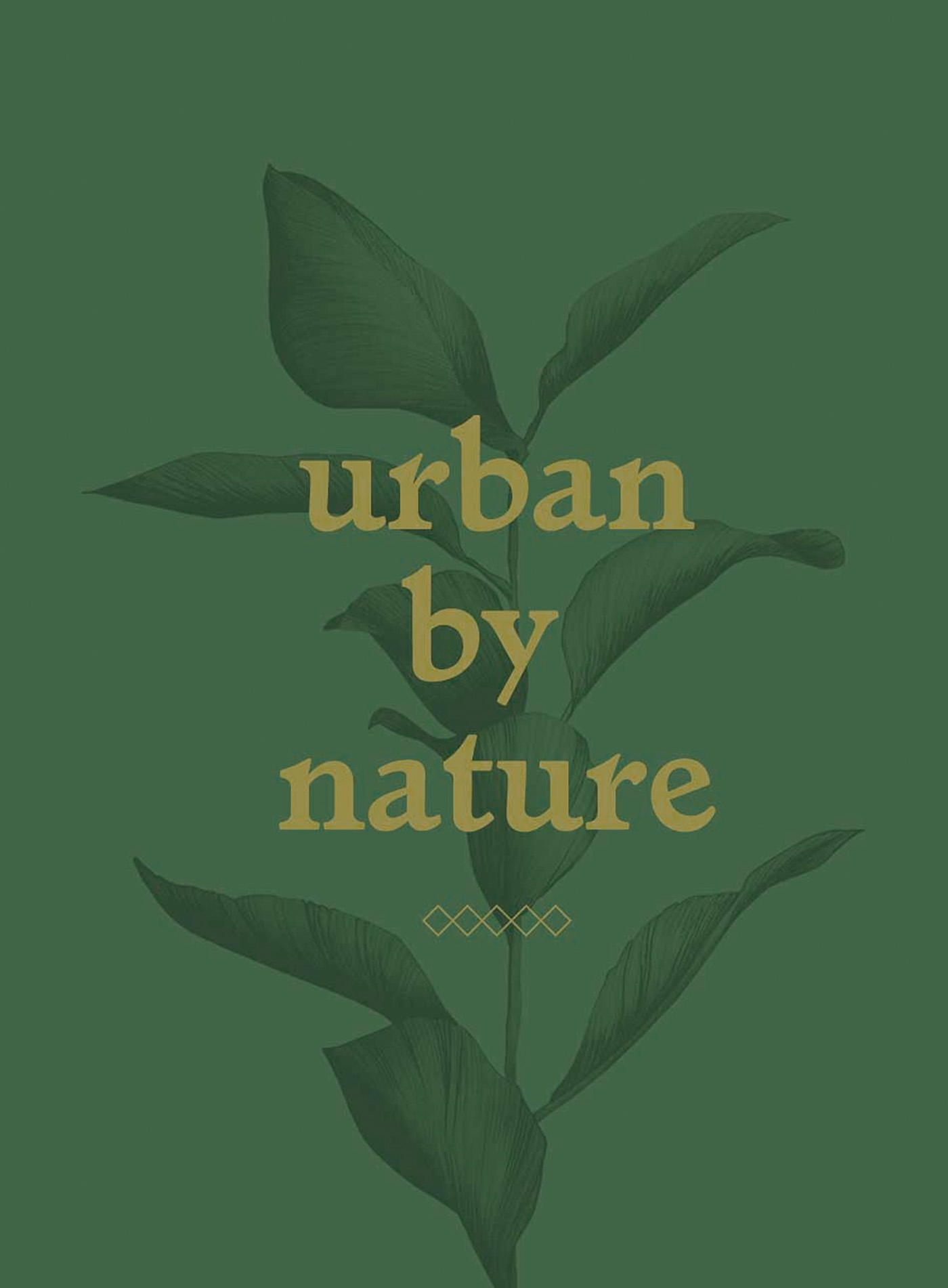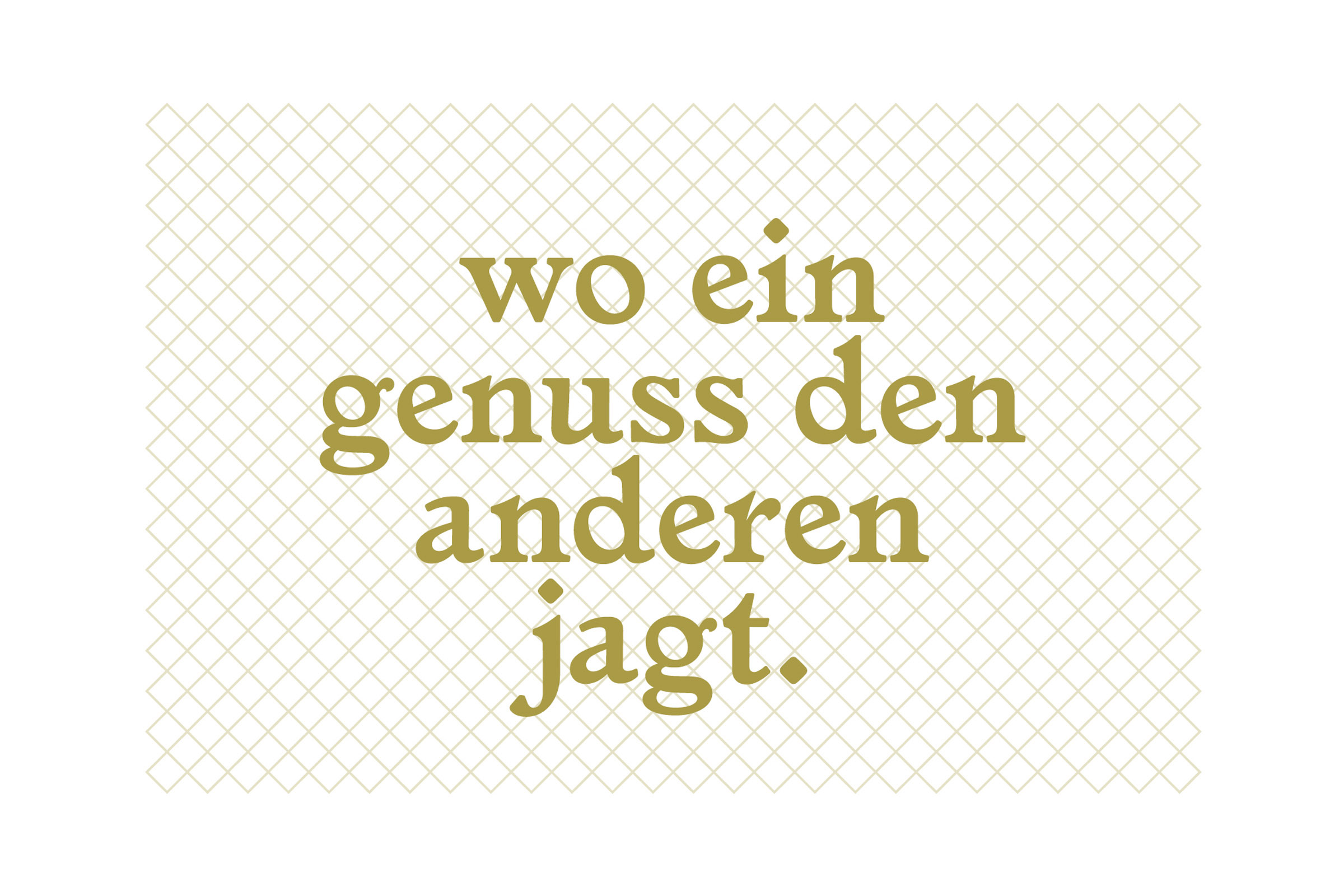
Suche Schriftnamen vom KITZ Boutique Hotel
Ich suche die Schriftart die für das Corporate Design für das KITZ Boutique Hotel in Metzingen verwendet wurde zu Recherchezwecken ggf auch den Kauf der Schrift. Meine bisherige Suche mit Fontsuchmaschinen war erfolglos. Vielleicht kann mir hier jemand weiterhelfen :)
Auf ihrer Website wird die Schriftart Volkhov genutzt, die der oberen aber nur ähnelt:   http://hotelkitz.de/de/